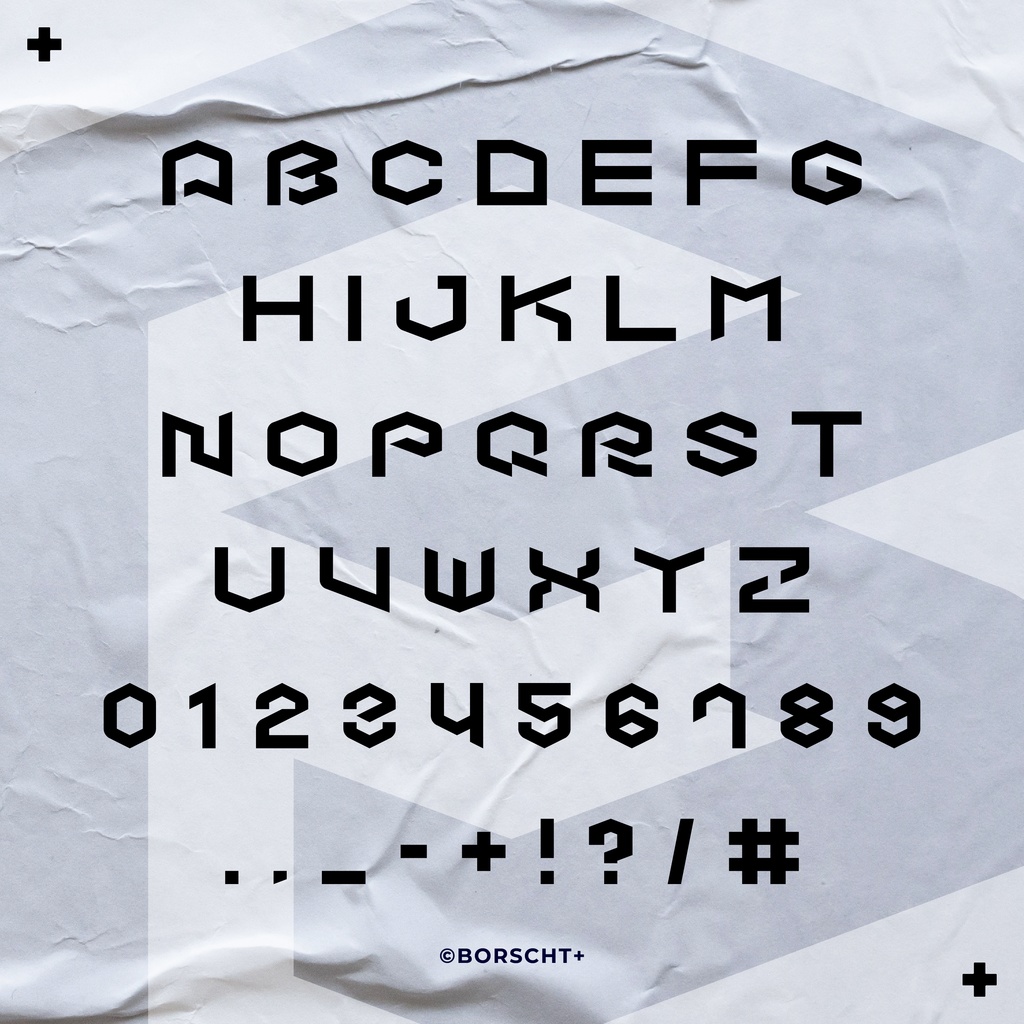
ビルドアップ・ボックス(フリーフォント)
○説明 「ビルドアップ・ボックス」(Build Up Box)は、積み上げられた箱のシルエットをモチーフにデザインした、サンセリフ体の欧文フォントです。字の幅が広く、安定した印象を与えます。 ○内容 ファイル形式:TrueType 収録文字:アルファベット26文字+数字+記号9種類(.,_-+!?/#) ○注意事項 ・このフォントは、個人・商用に拘らずご自由にお使いいただけます。 ・フォントデータの改変、二次配布はおやめください。 ・著作権は放棄しておりません。商標登録や作者を偽る行為はしないでください。 ・フォントのご使用に関連して生じた損害や第三者とのトラブルについて、BORSCH+(ボルシチ)は一切の責任を負いかねます。ご了承ください。 ○その他 ・使用報告、制作物へのクレジットは不要ですが、していただけると飛んで喜びます。Twitterでの拡散にご協力させていただきますので、お気軽にご記載ください(@BORSCHTofficialでメンションしていただけると反応しやすいです)。 ・「投げ銭」は、通常のダウンロード版と内容が変わりませんのでご注意ください。ご支援いただいた場合は、今後の活動資金に充てさせていただきます。 ・ご使用にあたり不明な点がありましたら、BOOTHのメッセージ、またはBORSCH+のTwitterDMまでご連絡ください。よろしくお願いいたします。 https://twitter.com/BORSCHTofficial